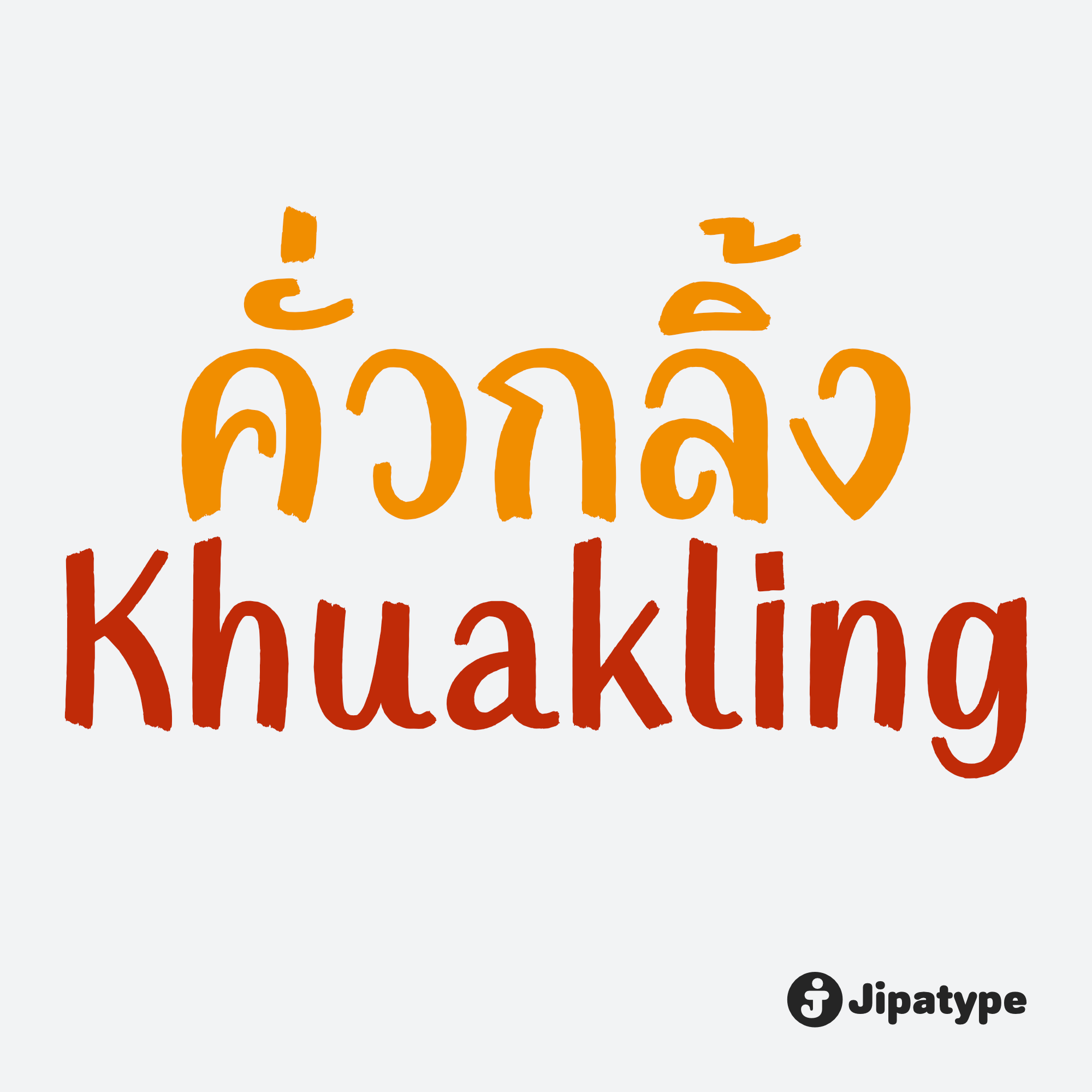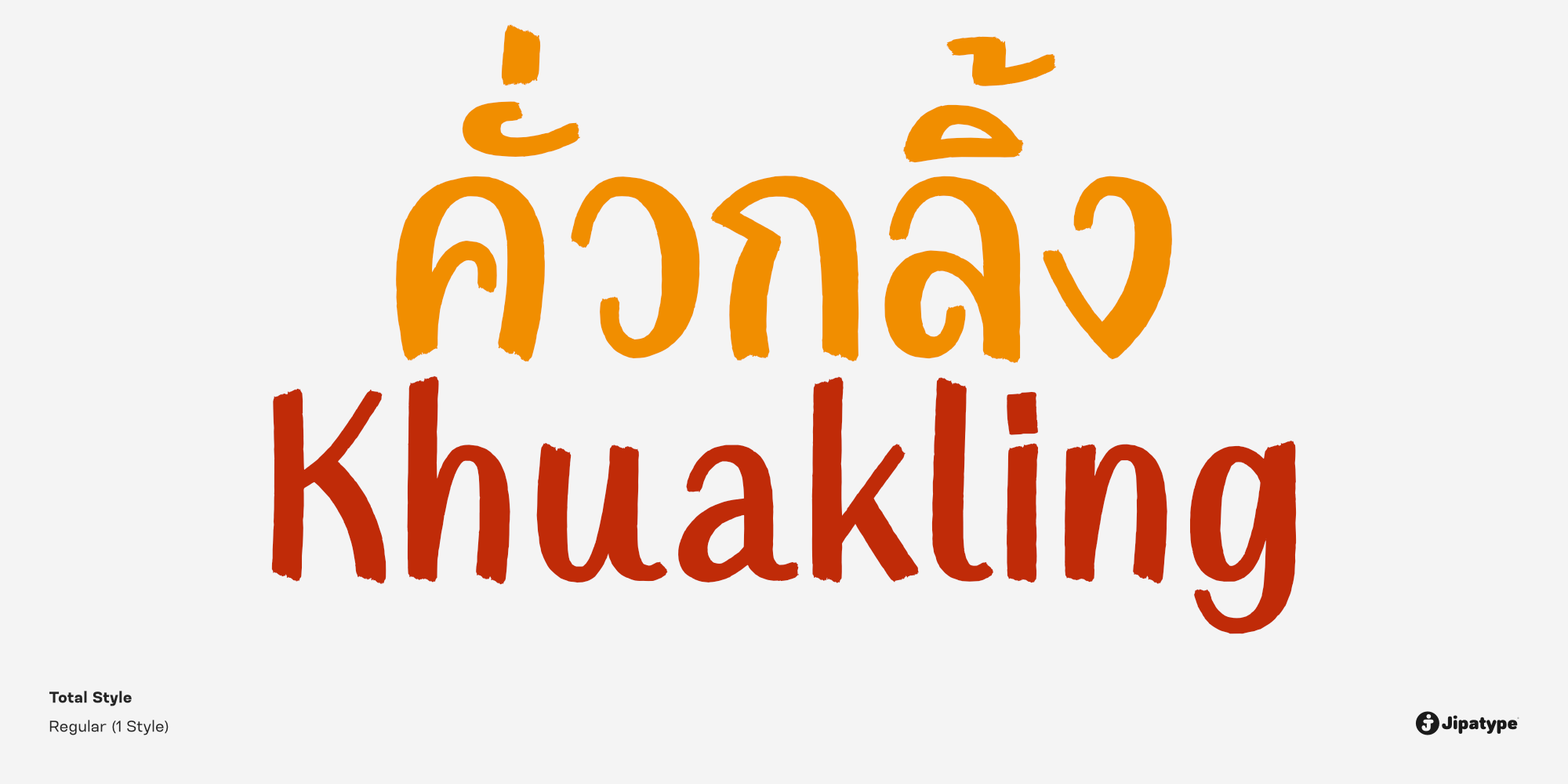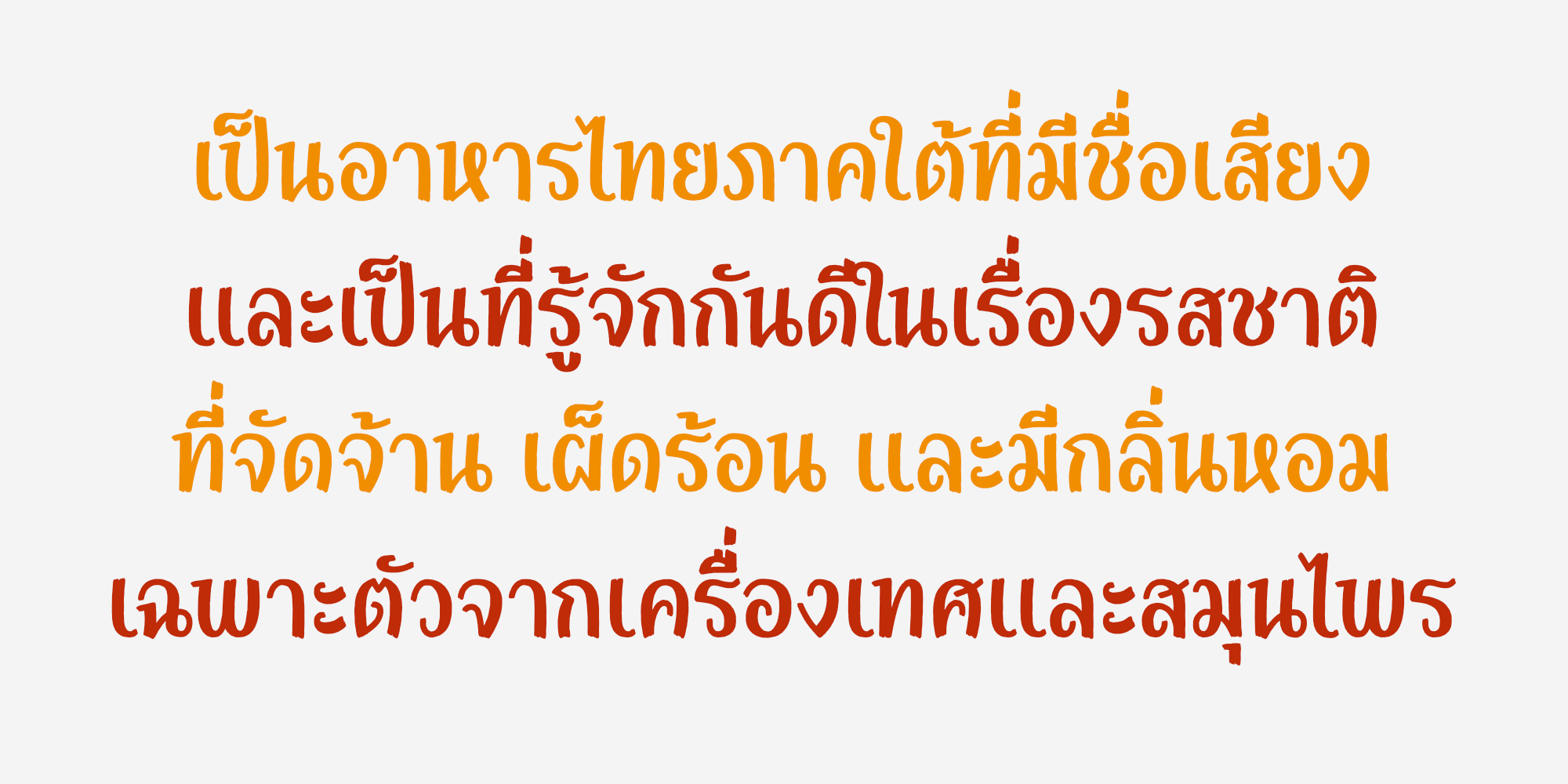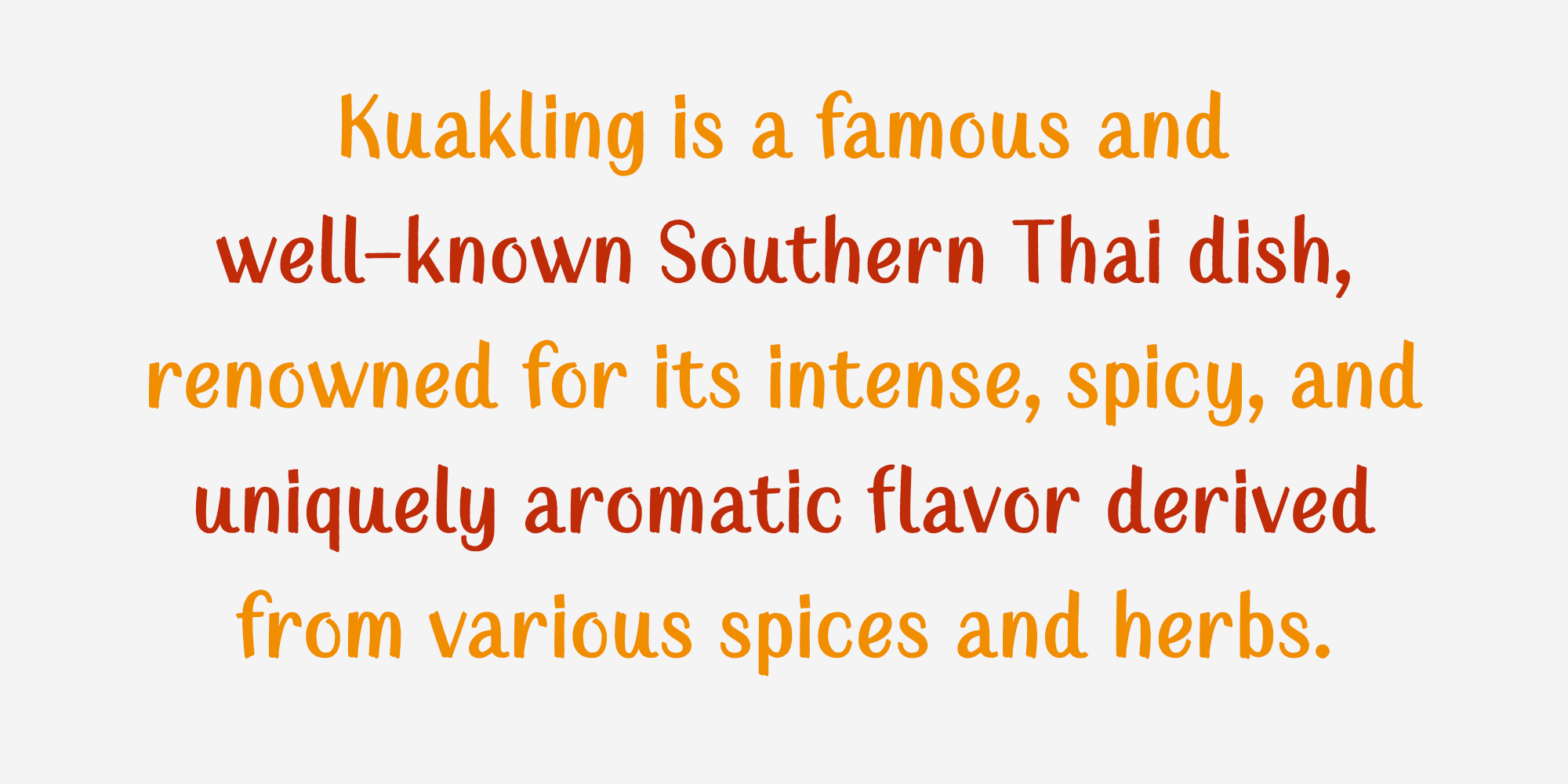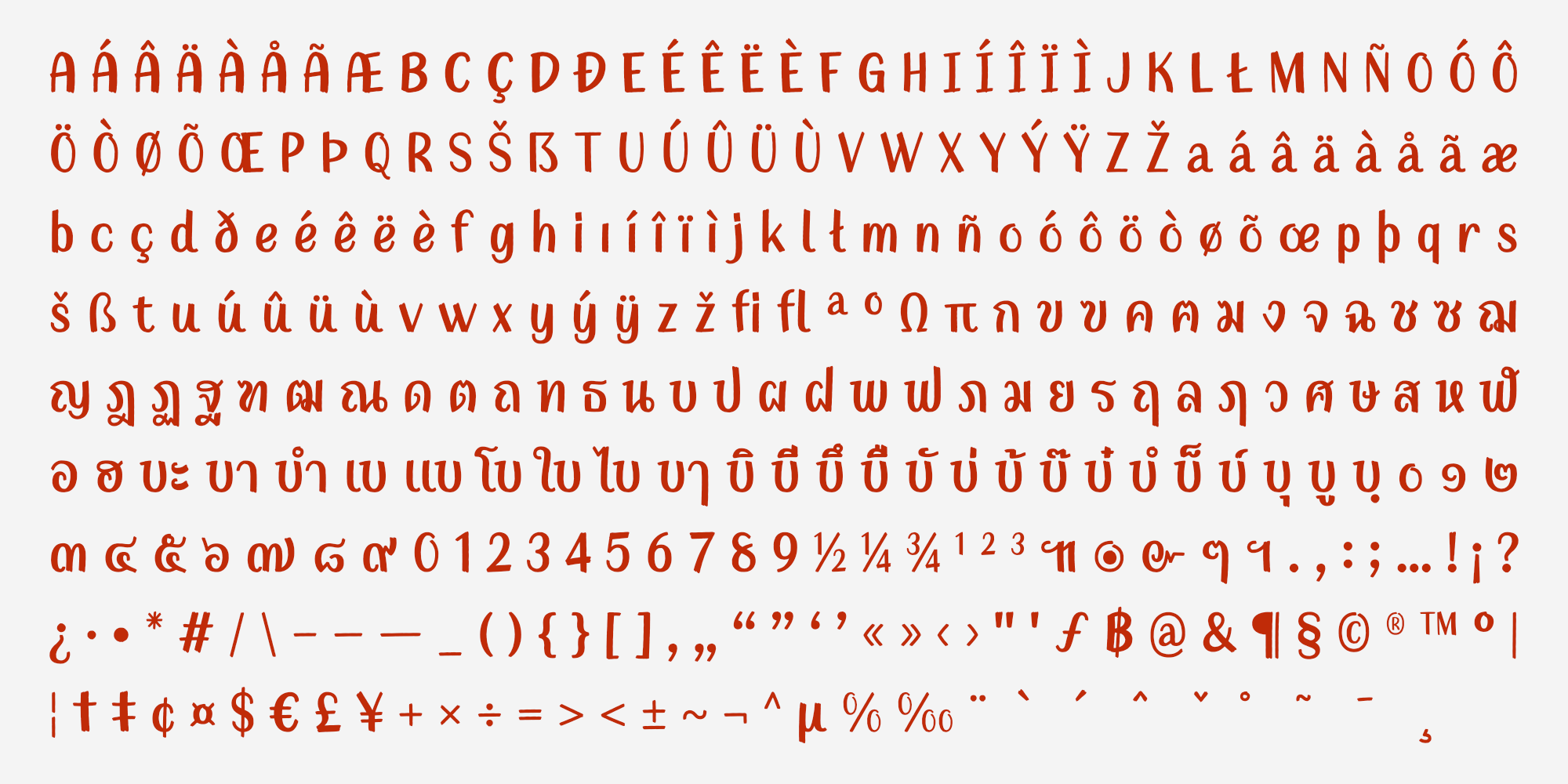
Khuakling เป็นฟอนต์ลายมือสไตล์พู่กันปลายตัดที่โดดเด่นด้วยลายเส้นอิสระดูเป็นธรรมชาติเสมือนการเขียนจริงด้วยพู่กันจริง ให้ความรู้สึกที่สนุกสนาน เป็นกันเอง และมีพลัง ด้วยน้ำหนักตัวอักษรที่หนาและเส้นขอบที่มีรายละเอียดความขรุขระเล็กน้อย ทำให้ตัวอักษรดูมีเท็กซ์เจอร์และไม่แข็งกระด้าง
จึงเหมาะอย่างยิ่งสำหรับการนำไปใช้เป็นพาดหัว งานออกแบบบรรจุภัณฑ์อาหาร เมนูร้านอาหาร ป้ายโฆษณา หรือสื่อโซเชียลมีเดียที่ต้องการสร้างภาพลักษณ์ที่ดูอบอุ่น เข้าถึงง่าย และสะดุดตาผู้อ่านได้ในทันที